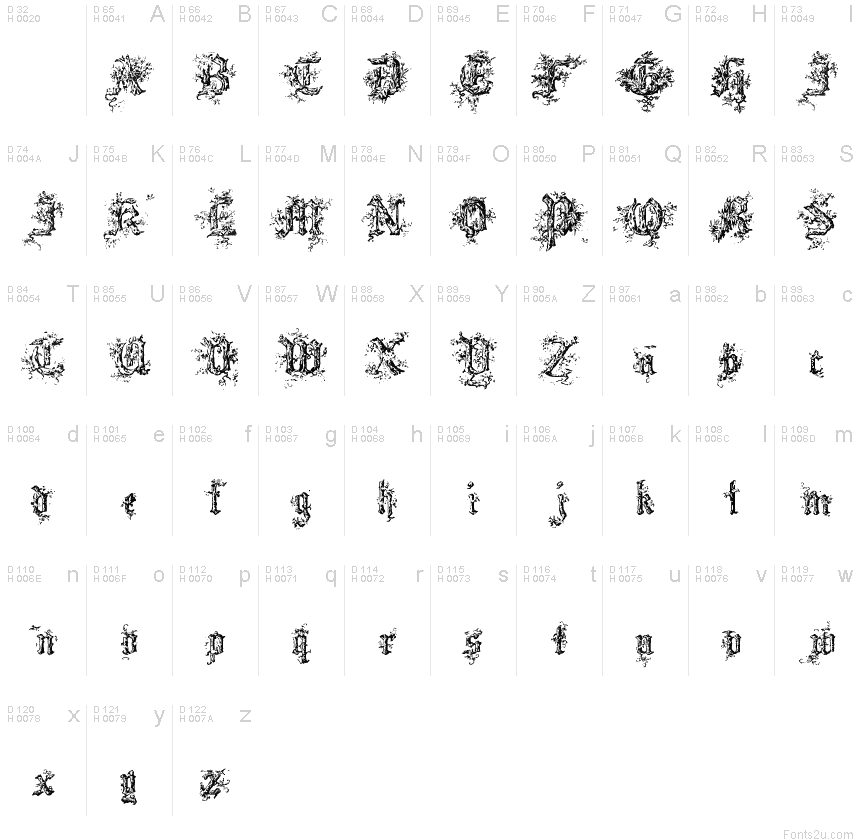
Black Forest di PJL è un font display gratuito e distorto, che ricorda una blackletter trascinata tra i rovi e nell'inchiostro fresco. I suoi tratti frastagliati e scheggiati appaiono spinosi e consumati, donando ai titoli un'atmosfera medievale feroce, come un monito inciso su una vecchia corteccia.
Black Forest è ideale per loghi di band metal, poster horror, inviti per Halloween, copertine di libri dark fantasy, merchandising occulto, volantini per attrazioni spettrali e schermate dei titoli di videogiochi. Usa Black Forest in grande formato e abbina questo font gratuito a un sans serif essenziale per il testo di accompagnamento, in modo che la texture ruvida rimanga nitida anziché diventare sfocata.